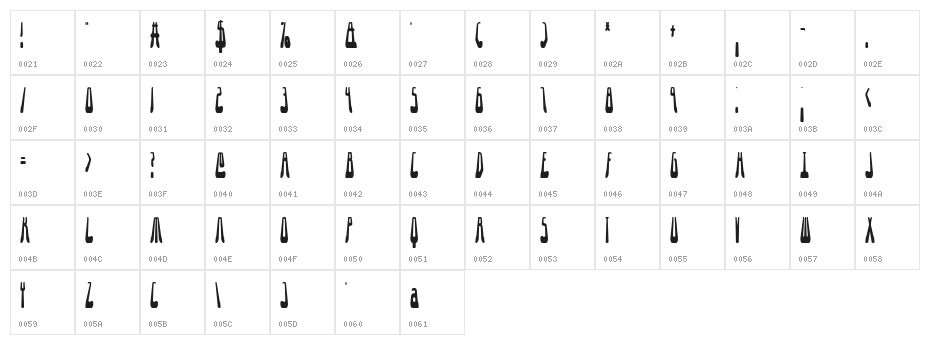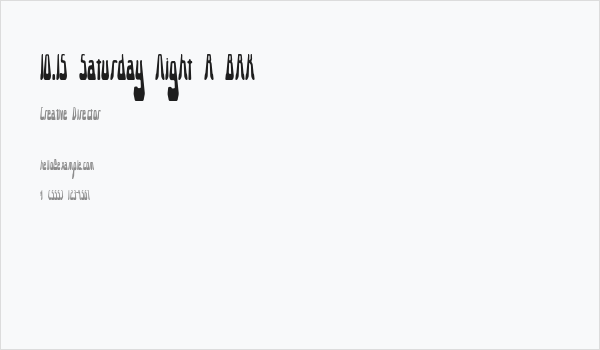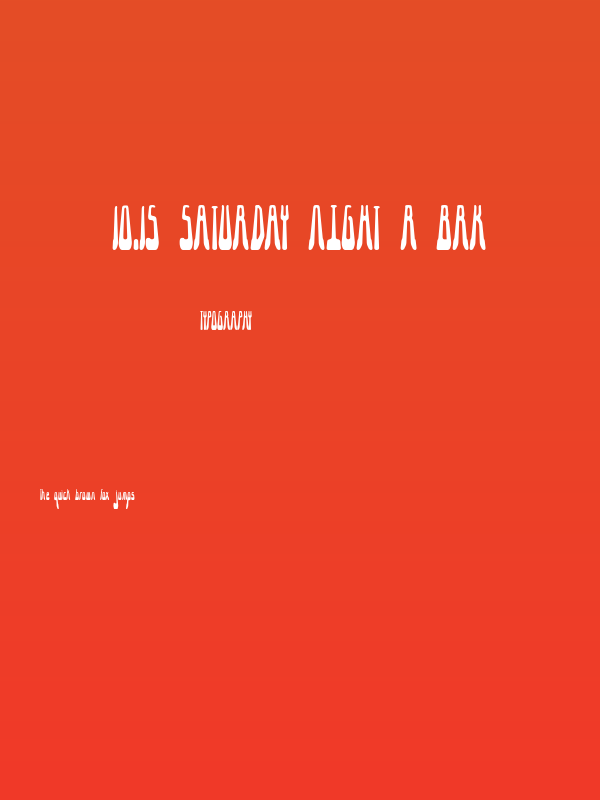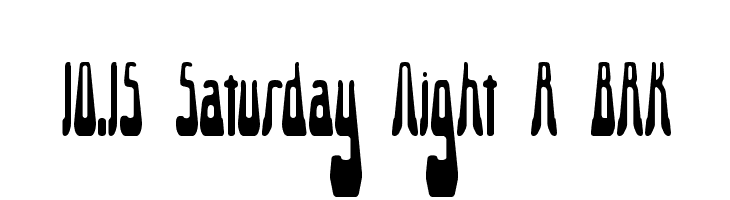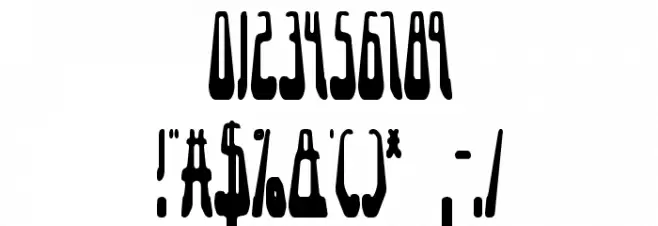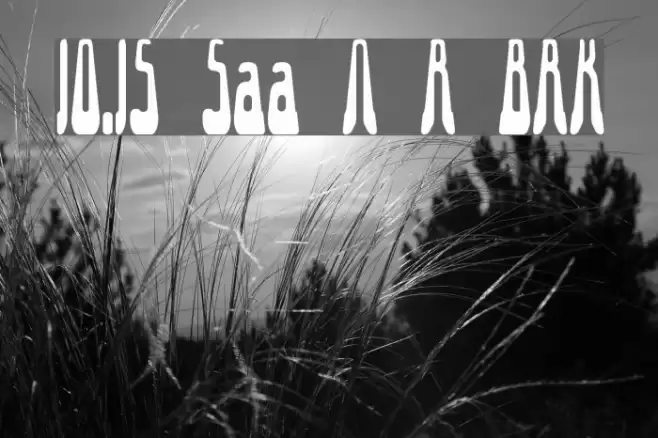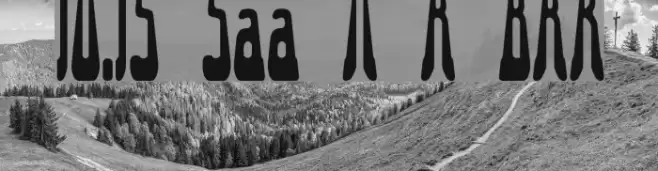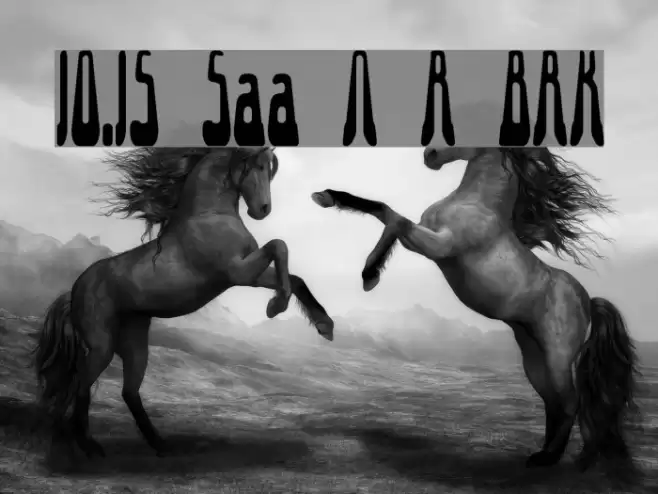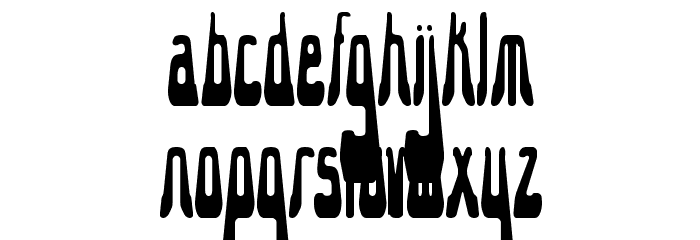
10.15 Saturday Night R BRK Font
| Proiecte propuse | Perfect for vintage-themed posters, album covers, and branding projects that require a bold statement. |